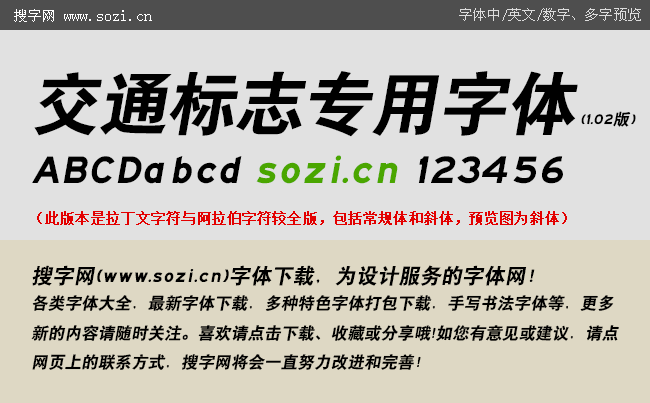
交通標(biāo)志專用字體字符較全版
搜字網(wǎng)提供一款交通標(biāo)志專用字體字符較全版中文字體下載,交通標(biāo)志專用字體是一款應(yīng)用于交通標(biāo)志的專用黑體,結(jié)構(gòu)端正、重心平穩(wěn)、美觀實(shí)用,并配有斜體效果,適用于包裝印刷、廣告設(shè)計(jì)、平面設(shè)計(jì)、書籍報(bào)紙等領(lǐng)域。